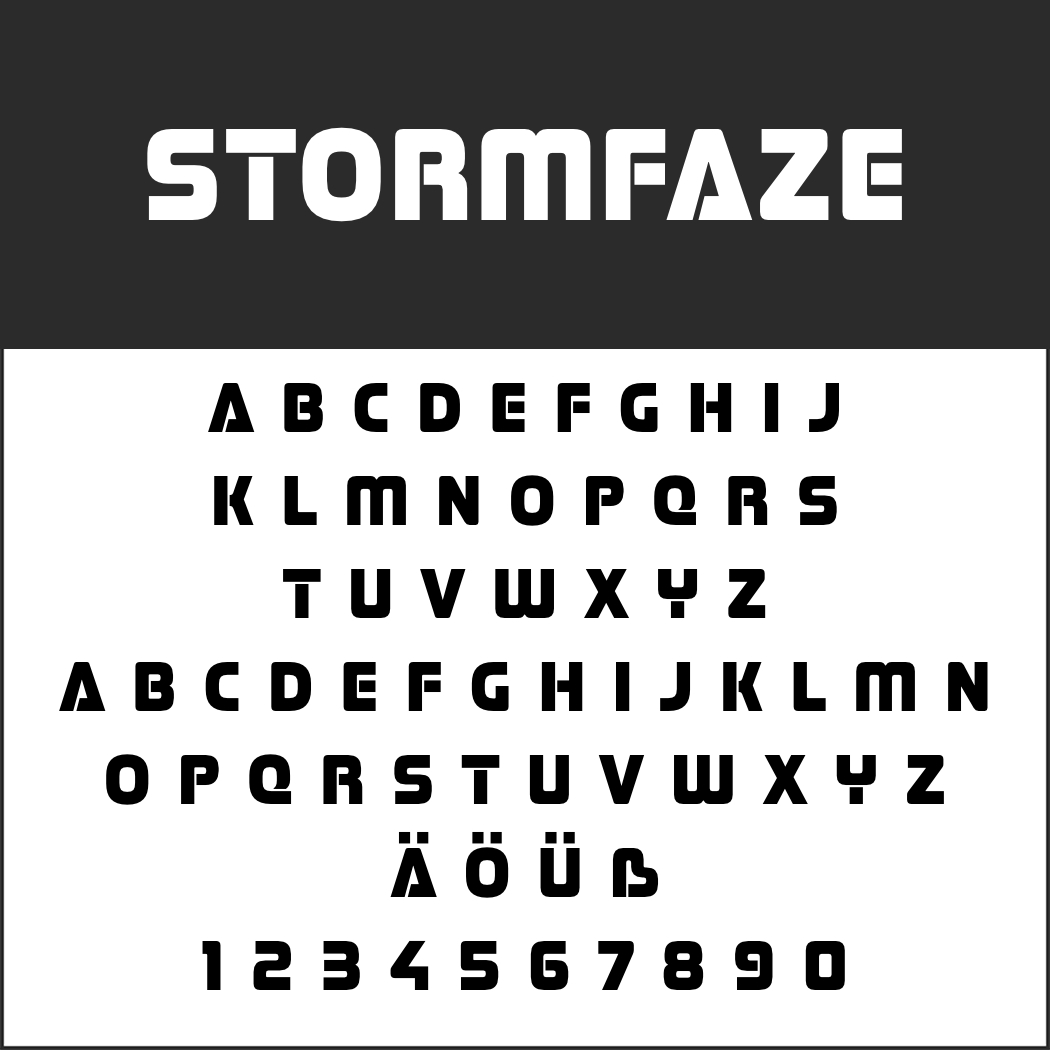
Die Schriftarten für Überschriften gibt es natürlich unzählige. In unserer Auswahl haben wir viele seriöse und einige schrillere Gratis-Fonts zusammengestellt.
Schriftarten für Überschriften zur kommerziellen Nutzung
Wenn Sie einen Klassiker suchen, sind Sie bei den ersten beiden Kategorien richtig: einmal Schriften mit, einmal ohne Serifen. Zum Abschluss zeigen wir Ihnen einige Beispiele mit etwas ausgefallenerem Stil.
Schriftarten für Überschriften mit Serifen
Schriftarten ÜberschriftenJenriv Titling
Das Paket von Jenriv Titling besteht aus drei Schriftstärken mit jeweils einer Kursiv-Variante.
Litoland
Litoland macht mit seinen sehr ausgeprägten Serifen einen überaus soliden Eindruck.
Schriftarten ÜberschriftenTitle Wave
Title Wave hat Schriftarten von Zeitungsüberschriften der 1940er Jahre zum Vorbild.
Volkhov
Die kontrastarme Serifenschrift ist besonders gut lesbar und deshalb neben Überschriften auch für Fließtext geeignet.
Yeseva One
Der Designer verlieh dieser Schriftart bewusst einen starken femininen Charakter. Der Name bedeutet „Yes, Eva“.
Schriftarten für Überschriften ohne Serifen
Schriftarten ÜberschriftenAsesine
Neben der Regular-Variante finden sich im Download-Paket auch eine dünne, eine superdünne und eine weite Version von Asenine.
Schriftarten ÜberschriftenGalderglynn Titling
Der Designer orientierte sich für diesen Font an verschiedenen serifenlosen Schriftarten des 19. Jahrhunderts.
Headline
Weich trotz eckiger Formen präsentiert sich Headline. Mehr in diesem Stil finden Sie unter Bubble-Schriften: fluffige Fonts zum Gratis-Download.
Jelle
Eine ganz runde Sache ist dieser Font von den Philippinen. Weitere Beispiele solcher Schriftarten haben wir unter Runde Schrift bringt Harmonie – zum Gratis-Download zusammengestellt.
Schriftarten ÜberschriftenKenzo
Die Schrift Kenzo macht sich gut auf Plakaten, vor allem, wenn relativ viel Text auf wenig Platz passen soll.
Headline-Schriftarten in speziellem Stil
AC Brodie
AC Brodie ist futuristischen Schriftarten aus den 1940er Jahren nachempfunden.
• Besonderheit: kein ß
Apex Mk2
Apex Mk2 basiert auf klassischen geometrischen Groteskschriften.
Schriftarten ÜberschriftenBlackout
Den Font Blackout gibt es in drei verschiedenen Stilen: nicht ausnehmend gut lesbar, aber auf jeden Fall ein Hingucker.
Headline Text
Die Schrift mit dem treffenden Namen Headline Text erinnert an Überschriften in traditionellen Zeitungen. Weitere Beispiele finden Sie unter Gebrochene Schriften zum kostenlosen Download.
Holtwood One SC
Dieser Font ist Holzschnittarten aus dem 19. Jahrhundert nachempfunden.
• Besonderheit: keine Kleinbuchstaben
Palamecia Titling
Die Unregelmäßigkeiten dienen einer höheren Lesbarkeit bei jeder Auflösung. Mehr Comic-Fonts finden Sie unter Comic-Schriftarten zum kostenlosen Download.
Stormfaze
Titel von Actionfilmen der 1980er Jahre lieferten die Vorbilder für diesen Font.
TM Unicorn
Dieser Font ist bisschen Art déco, ein bisschen 1950er, auf jeden Fall Retro.